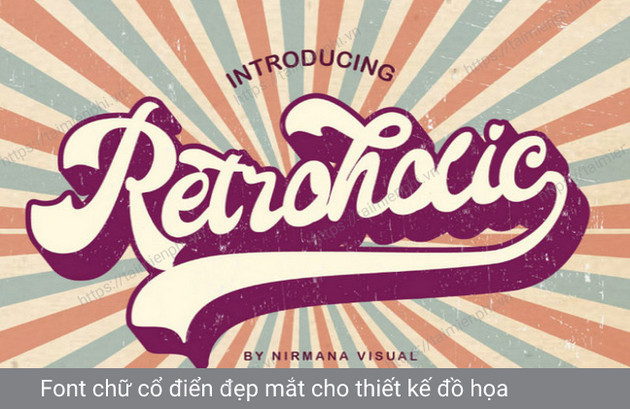
Font chữ Retro
Download Font chữ Retro - Font chữ cổ điển đẹp mắt cho thiết kế đồ họa
Font chữ Retro phù hợp cho những nhà thiết kế yêu thích vẻ đẹp hoài cổ. So với các font chữ hiện đại khác, font chữ Retro mang đến sự độc đáo và chiều sâu văn hóa, giúp bạn tạo nên những tác phẩm ấn tượng với phong cách cổ điển hài hòa.
Với sự kết hợp hoàn hảo giữa các yếu tố lịch sử và xu hướng thiết kế hiện đại, font chữ Retro mang đến cho bạn phong cách thiết kế độc đáo và ấn tượng. Được nhiều nhà thiết kế đồ họa ưa chuộng, font chữ này dễ dàng điều chỉnh mà không làm mất đi cấu trúc của tác phẩm. Một minh chứng tiêu biểu cho thành công của font chữ Retro là bộ phim Cô Ba Sài Gòn, nơi mà font chữ đã góp phần tạo nên không gian văn hóa Sài Gòn những năm 50-60.
Tính năng nổi bật
- Phong cách thiết kế cổ điển: Mang đến sự quyến rũ và độc đáo cho các tác phẩm.
- Dễ dàng tùy chỉnh: Có thể điều chỉnh linh hoạt mà không phá vỡ cấu trúc ban đầu của tác phẩm.
- Tính ứng dụng cao: Phù hợp cho nhiều dự án thiết kế khác nhau, từ quảng cáo đến bộ phim.
- Gợi nhớ ký ức: Kết hợp giữa quá khứ và hiện tại, tạo nên cảm giác hoài niệm.
Bằng việc lựa chọn font chữ Retro, bạn sẽ có trong tay công cụ tạo nên những bản thiết kế không chỉ hiện đại mà còn mang đậm dấu ấn văn hóa ấn tượng.